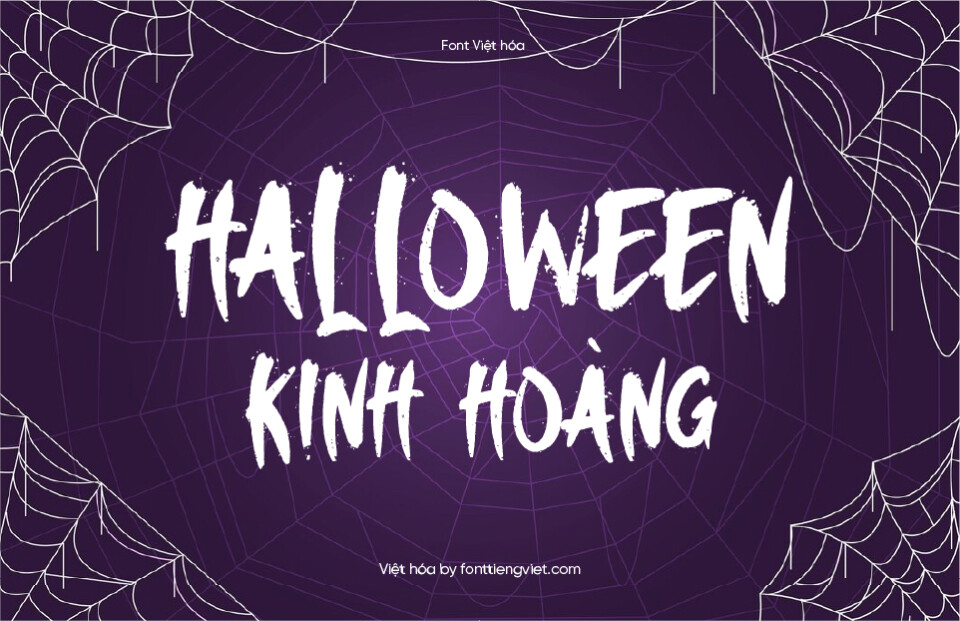
Font Việt hóa 1FTV VIP Zombies Brainless – Halloween
Giới thiệu về bộ Font Việt hóa 1FTV VIP Zombies Brainless – Halloween
Mùa lễ hội hóa trang đang đến gần và việc tìm kiếm một mẫu Font Miễn Phí mang phong cách rùng rợn là ưu tiên hàng đầu của các nhà thiết kế. Font Việt hóa 1FTV VIP Zombies Brainless – Halloween chính là lựa chọn hoàn hảo để tạo nên sự đột phá cho các ấn phẩm truyền thông. Với những đường nét đứt gãy, thô ráp và mang đậm hơi hướng “xác sống”, bộ font này giúp truyền tải thông điệp ma mị một cách mạnh mẽ nhất. Đây là một trong những font chữ thuộc phân khúc cao cấp đã được đội ngũ 1FTV tinh chỉnh tỉ mỉ để phù hợp với bảng mã tiếng Việt.
Đặc điểm nổi bật của font chữ Halloween độc đáo
Sức hút của Font Việt hóa 1FTV VIP Zombies Brainless – Halloween nằm ở sự kết hợp giữa tính nghệ thuật và sự kinh dị. Các ký tự được thiết kế không đồng nhất, mô phỏng hình ảnh não bộ hoặc những vết cào xé, tạo cảm giác rùng rợn ngay từ cái nhìn đầu tiên. Font chữ này không chỉ phục vụ cho mục đích giải trí mà còn rất hữu ích trong giáo dục, giúp học sinh thực hiện các dự án sáng tạo về chủ đề văn hóa phương Tây hoặc thiết kế thiệp mời cho các buổi tiệc ngoại khóa tại trường học.
Cách ứng dụng Font Việt hóa 1FTV VIP Zombies Brainless – Halloween hiệu quả
Để tối ưu hóa vẻ đẹp của Font Việt hóa 1FTV VIP Zombies Brainless – Halloween, bạn nên sử dụng nó cho các tiêu đề lớn, banner quảng cáo hoặc poster phim kinh dị. Việc kết hợp font này với các tông màu tối như đen, đỏ máu hoặc cam neon sẽ làm nổi bật hiệu ứng thị giác. Lưu ý rằng do tính chất nghệ thuật đặc thù, bạn không nên sử dụng font này cho các đoạn văn bản dài để đảm bảo tính dễ đọc cho người xem. Hãy tận dụng sự độc đáo của nó để tạo điểm nhấn cho bìa sách, áo thun hoặc các sản phẩm thủ công Halloween.
Lợi ích khi sử dụng font chữ đã được Việt hóa
Việc sử dụng Font Việt hóa 1FTV VIP Zombies Brainless – Halloween giúp các bạn học sinh và giáo viên tiết kiệm thời gian trong việc xử lý lỗi font khi gõ tiếng Việt có dấu. Sự tương thích hoàn hảo này giúp quy trình thiết kế trở nên mượt mà và chuyên nghiệp hơn. Bạn có thể dễ dàng tải xuống và cài đặt bộ chữ này trên các phần mềm đồ họa phổ biến để bắt đầu hành trình sáng tạo của mình ngay hôm nay.